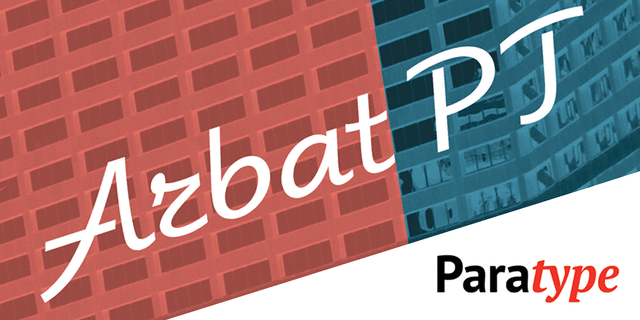
Apbat PT — каллиграфический шрифт, разработанный по мотивам шрифта Elite Альдо Новарезе (Aldo Novarese). Пластика и элегантность форм определяют возможность использования шрифта в рекламных материалах, акциденции, коротких текстах и упаковке. Новая цифровая версия Arbat PT разработана Изабеллой Чаевой и выпущена компанией Паратайп в 2018 году.
Ассоциации c семейством ArbatКачества и характер:
легкомысленный, праздничный, молодежный, прямодушный, щедрый, гостеприимный, радостный, позитивный, вежливый, весенний, счастливый